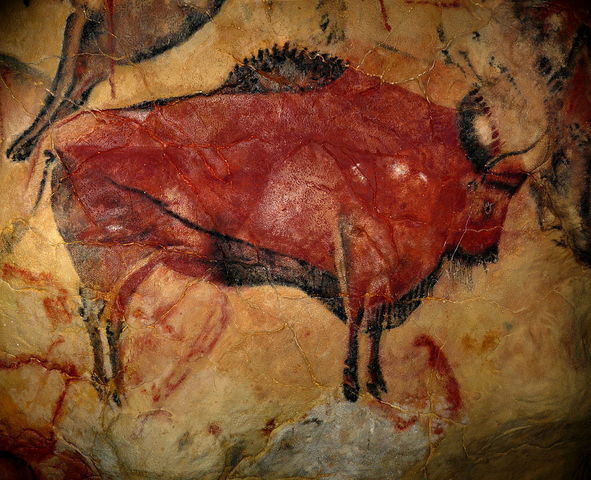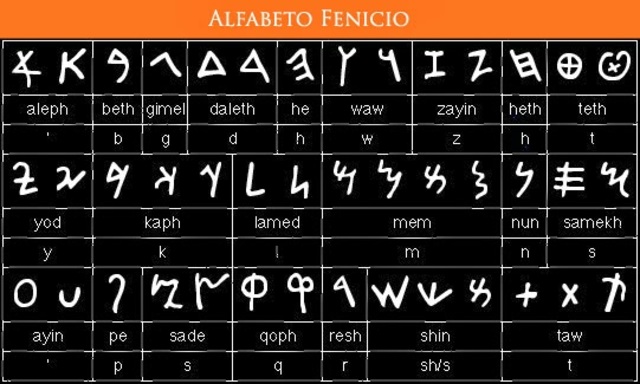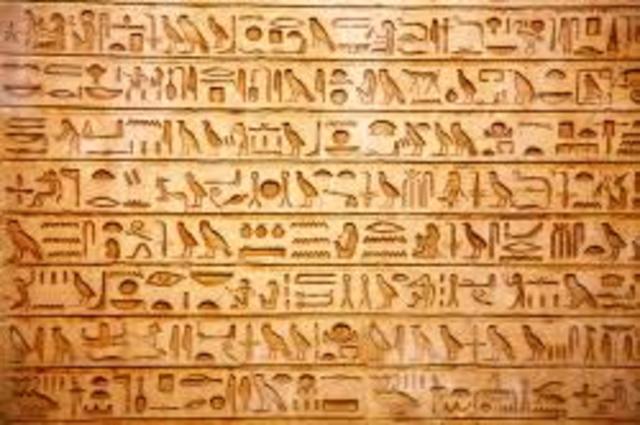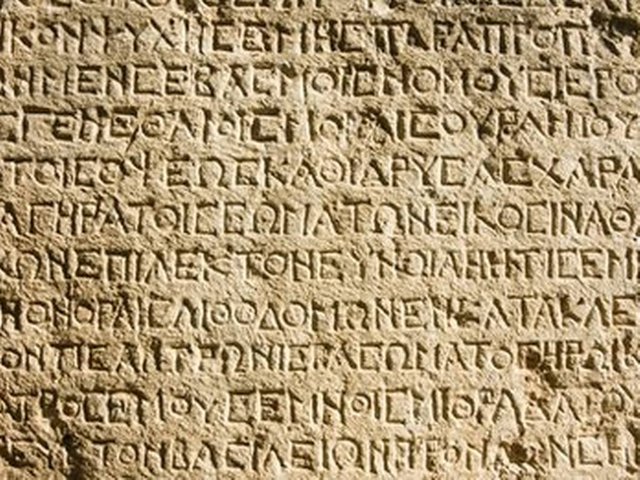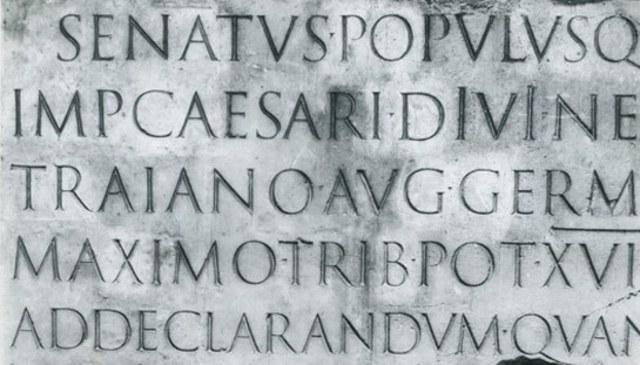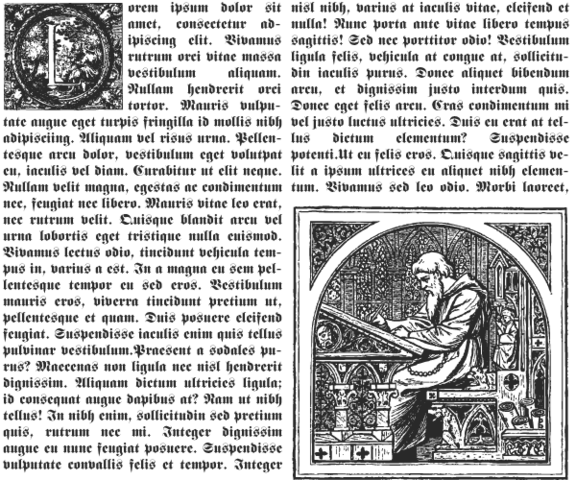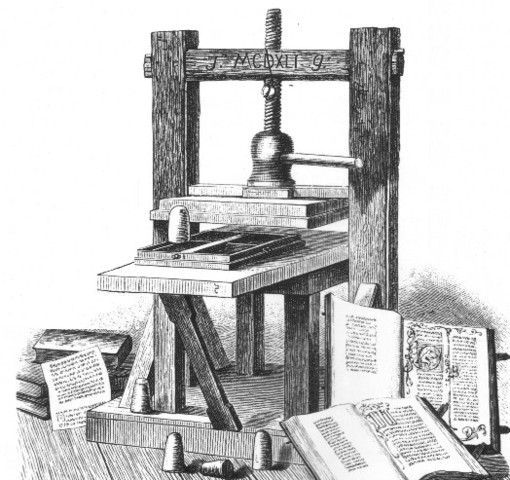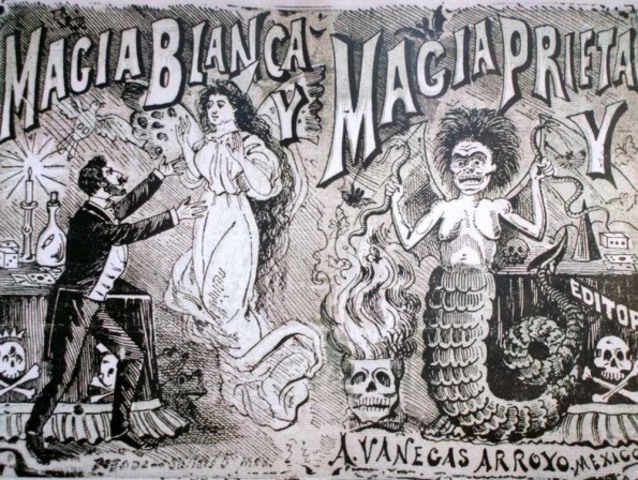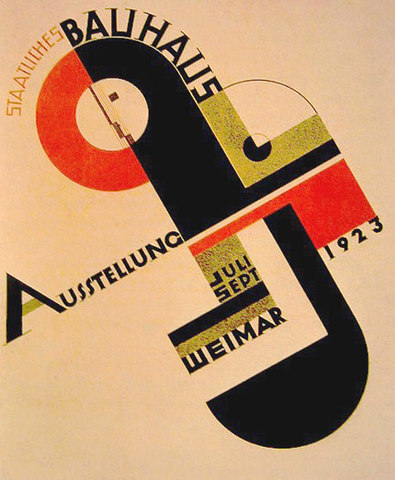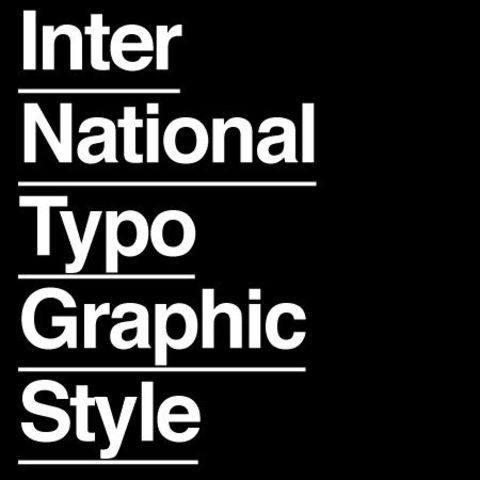
representaciones de la vida prehistórica talladas en piedras o cavernas, primeras formas representación pictórica
primeros indicios de escrituras, los Sumerios plasmaron pictogramas en tablillas de arcilla que simbolizaban palabras y objetos
aparece en el antiguo Egipto, basada en pictogramas que constituían a su vez un símbolo, aparición por primer a vez del papiro, como remplazo de la arcilla
una de las primeras formas de alfabeto, constaba de 22 simbolos, cada uno con su propio fonema, se convierte en el tipo de escritura predominante, gracias a los mercaderes fenicios
primer alfabeto de la historia, 24 letras con la aparición de las vocales, en donde cada vocal y cada consonante corresponde a un símbolo especifico(surge a raíz del alfabeto fenicio)
surge a raíz del alfabeto griego, aparece el concepto de mayúsculas. Surge la tabla de cera que permitía borrar
es la base del sistema alfabético moderno -
surge el pergamino como remplazo del papiro, creación letra gótica, aumento de la lectura, gracias a la aparición de múltiples universidades
Johannes Gutenber, crea la imprenta con tipos móviles, con la cual se masifico la producción de libros en papel, con esto aparecen las primeras fuentes
la aparición de grandes metrópolis, despliega la aparición de un sin fin de carteles publicitarios y por su puesto de la prensa escrita, así aparecen la prensa mecánica, la litografía y la linotipia entre otras, como fusión del arte y la producción en masa
utilización de formas rectangulares y colores primarios
creación de fuentes pensadas en diferentes tipos de usos, aparece la elaboración de carteles cada vez mas elaborados, en pro del consumismo y la comercialización
daba un enfoque centrado en la funcionalidad
basada en los conceptos de funcionalidad de los años 20
formatos de gran tamaño, con ornamentación exagerada, mas enfocados a asociaciones o referencias que a su legibilidad
con la llegada de las nuevas tecnologías, a través de los ordenadores personales, se masifica el acceso a la tipografía, paso de las lecturas en papel a las lecturas en dispositivos móviles